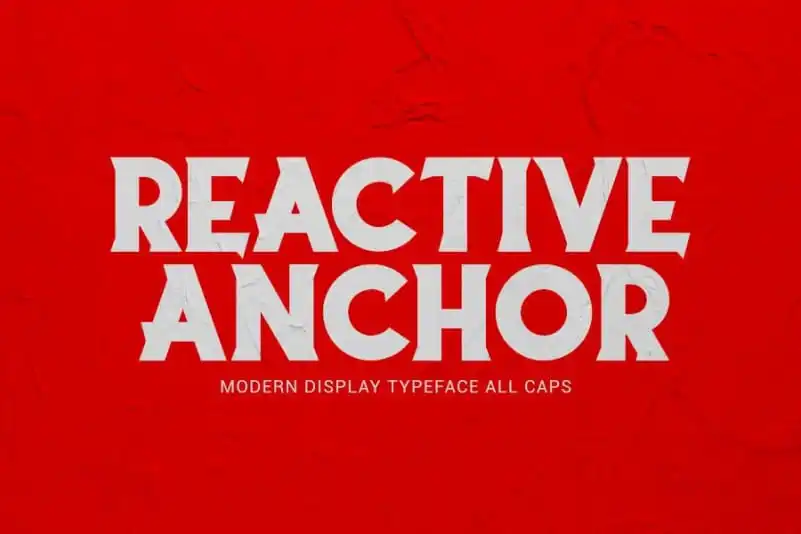
Reactive Anchor Display Font
A fonte ‘Reactive Anchor Display Font’ oferece uma experiência visual moderna e futurista. Inspirada no estilo do tipo sans-serif, ela traz formas acuradas e linhas afiadas que são perfeitas para criar logotipos ou design gráfico contemporâneo. Sua estrutura minimalista não apenas encaixa-se perfeitamente em uma variedade de aplicações, mas também aprimora o impacto visual de qualquer projeto. Com um toque arrojado e moderno, você pode destacar sua marca com um estilo inovador e único. Seja para aplicativos online ou impressos, esta fonte garante que seu design seja instantaneamente reconhecível. A ‘Reactive Anchor Display Font’ da 99designs é uma opção ideal para quem procura uma fonte de destaque que traga um toque moderno e inovador ao seu trabalho.